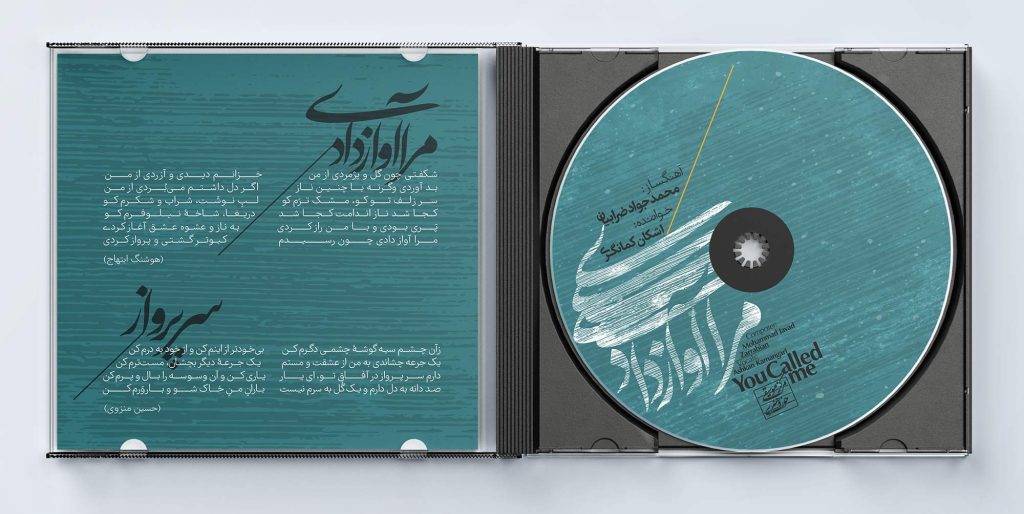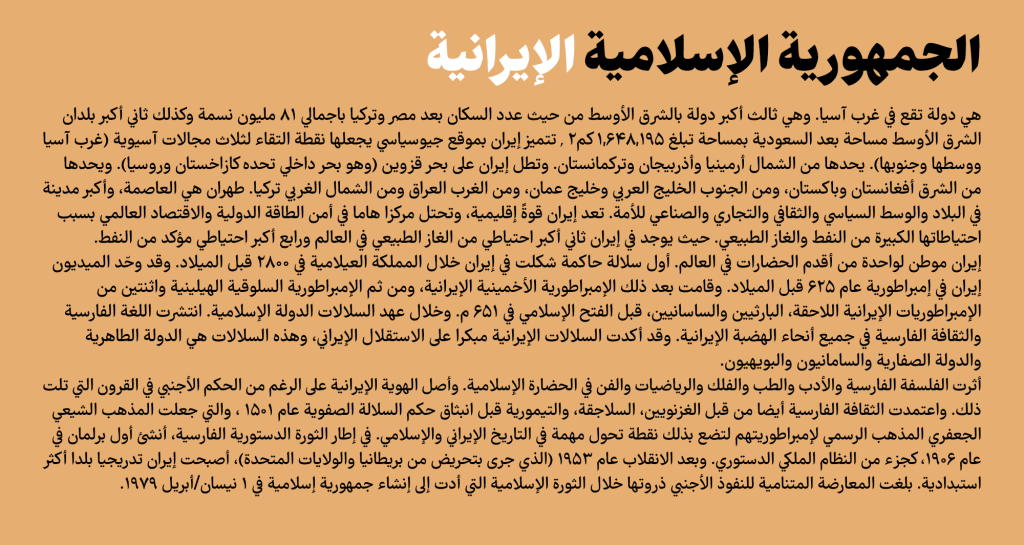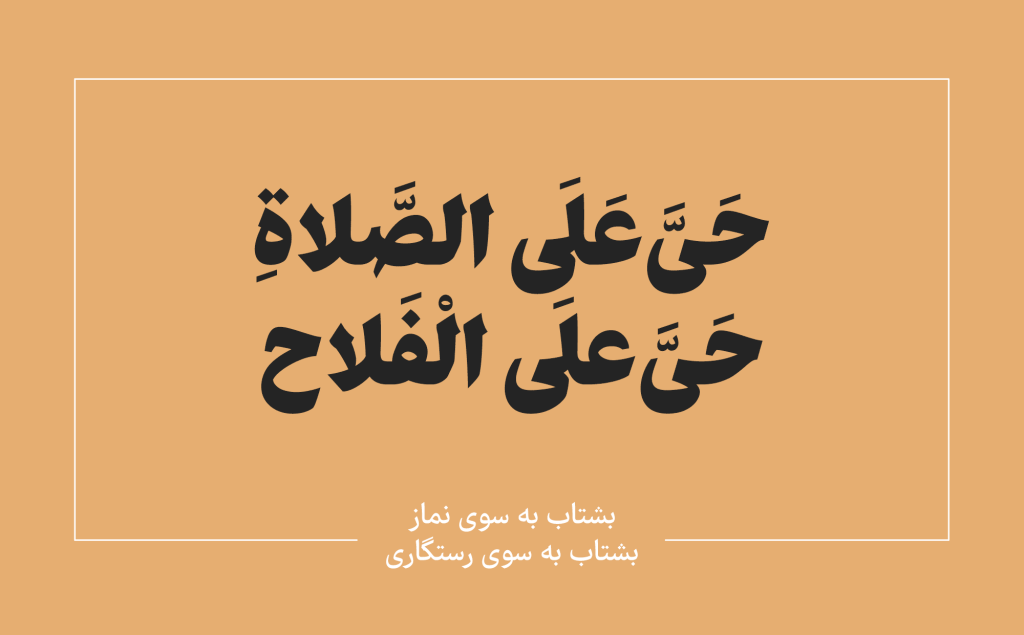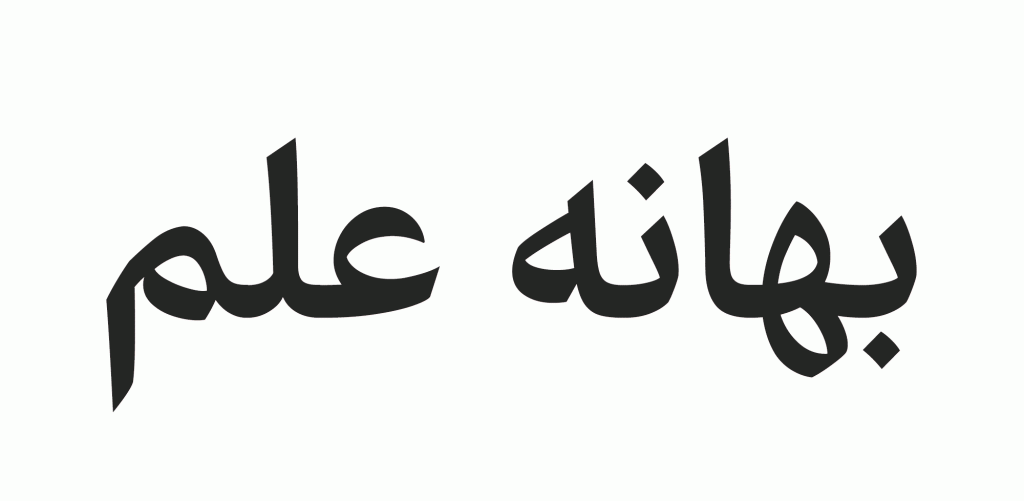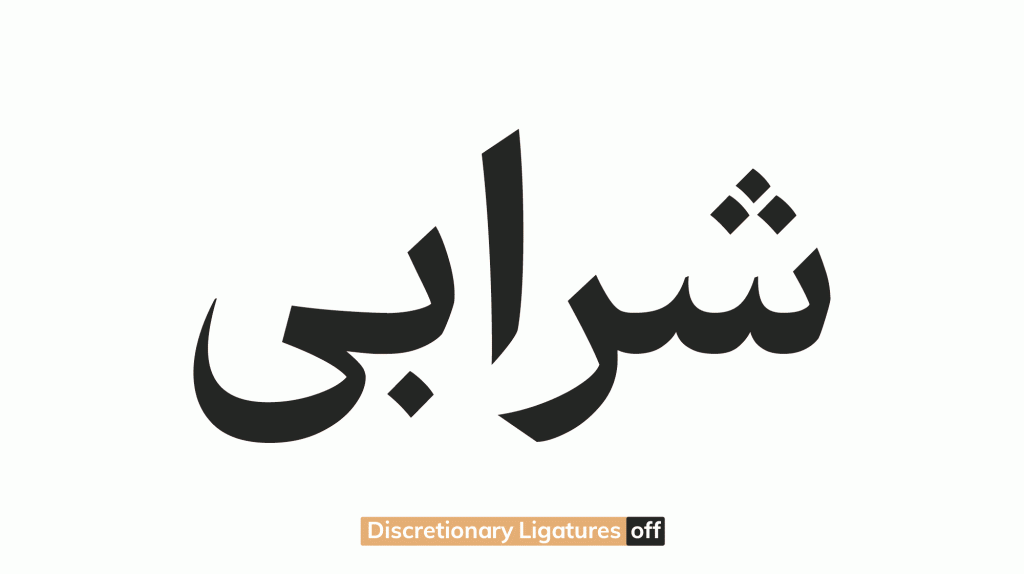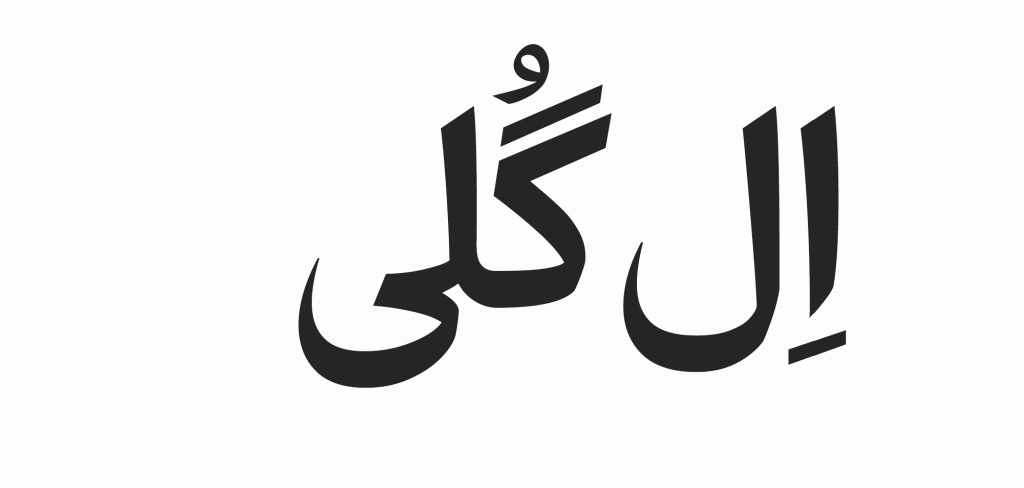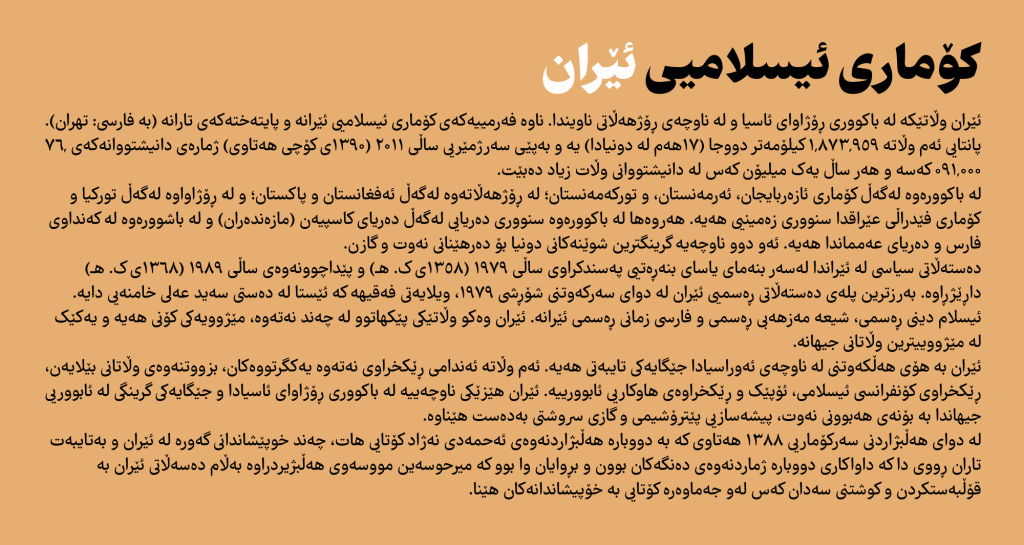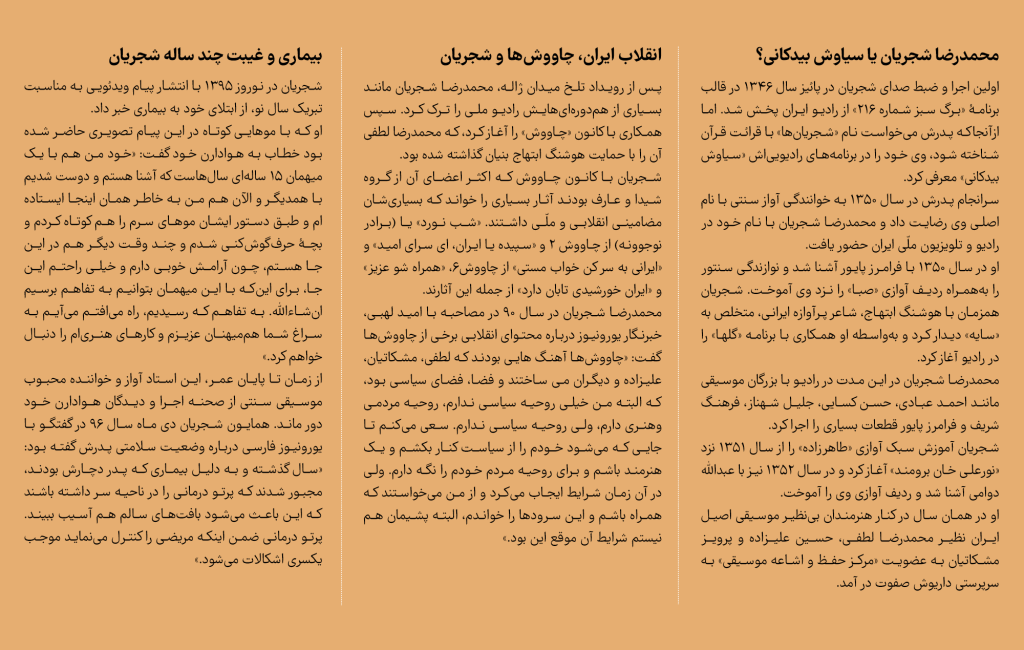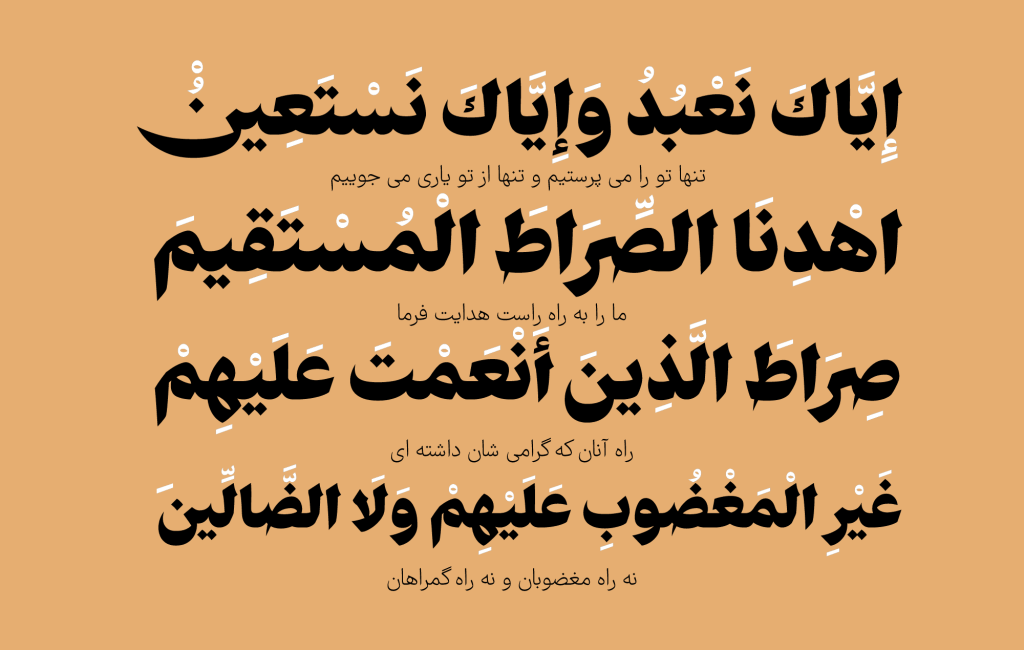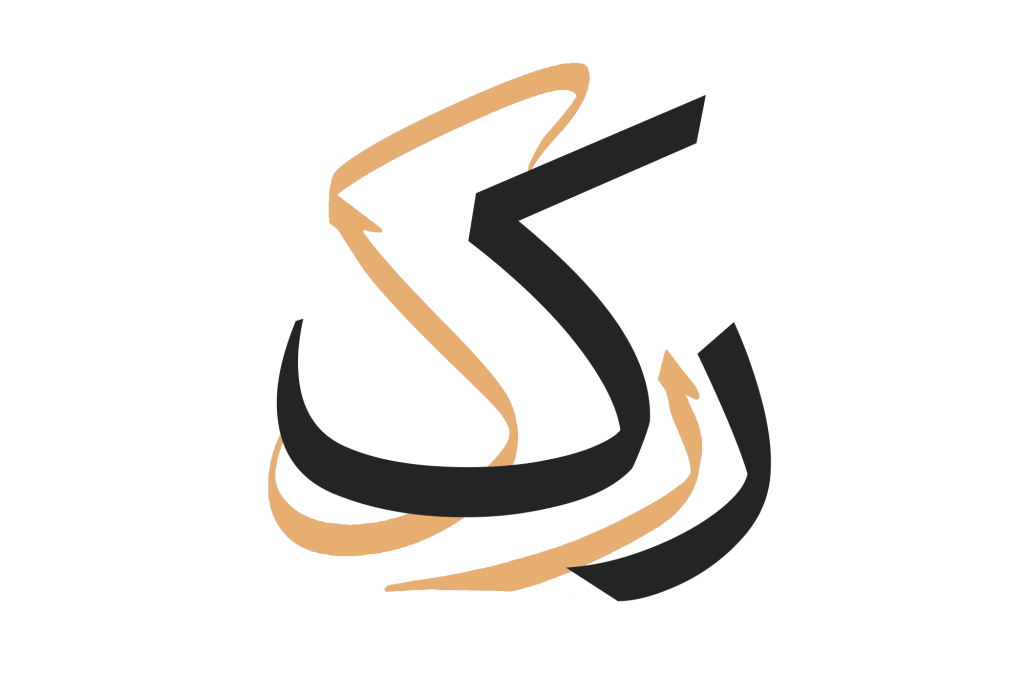
فونت آهنگ
فونت آهنگ قلمی که الهام گرفته از خانواده نسخ و ثلث است توسط آقای مسلم ابراهیمی طراح نام آشنای تایپوگرافی فارسی ایجاد و طراحی گشته است. در واقع این تایپ فیس نسخه بازسازی شده ای از فونت زیبای فرهنگ به همراه 10 وزن متفاوت و بسیاری از امکانات برای شما علاقه مندان و طراحان است.
در بسته دانلود شده این محصول دو سبک یا استایل اصلی و شارپ وجود دارد. آهنگ شارپ در واقع پایه اصلی این محصول زیبا است و فونت آهنگ با تخت کردن و کاهش کنتراست استایل آهنگ ‌شارپ پدید آمده است.
خطاطی و خوشنویسی در قلم آهنگ
از دیر باز حروف  ” ر – ک ” دو حرف پرچالش برای طراحان تایپوگرافی به شما رفته است. چرا که همواره باید مواظب آن بود که تجاوزی به همسایگان خود نداشته باشند. اما در این تایپ فیس به منظور حفظ حس و حال خطاطی و زیبایی کار این حروف یعنی ک و ر ، پاشنه بلند و سرکش هستن بدون  اینکه هرکدوم  پاشو از گلیم خودش درازتر کرده یا سرک کشیده باشن به فضای حرف همسایه.
با دقت در تصاویر نمونه از این تایپ فیس به تفاوت هایی مشهود بین دوسبک از این قلم پی می بریم. آهنگ دندانه‌های تخت دارد، با صلابت و قدرتمند است. در صورتی که آهنگ شارپ (با تیز شدن دندانه‌ها و انتهای حروف) به دنبال حفظ اصالت خطاطی و ظرافت هنری می باشد
در اوزان پایین‌ چندان تفاوتی بین  آهنگ و آهنگ شارپ مشاهده نمی شود و بیشتر جنبه کاربردی دارد. وجود دو استایل متن با کنتراست متفاوت به طراحان این امکان را می‌دهد که با توجه به نوع کاغذ و چاپ یا شرایط نمایشگر دیجیتال نسخه سیاه‌تر (آهنگ) یا نسخه ظریف‌تر (اهنگ شارپ) را انتخاب کنند.
پشتیبانی فونت آهنگ از ترکیبات جایگزین
به منظور ایجاد تنوع و زیبایی دو چندان ترکیبات جایگزین در قلم آهنگ تعیین گردیده است. آهنگ دارای تعدادی از ترکیبات جایگزین و اختیاری است که دست طراحان را برای خلق تنوع و دوری از یکسانی و یکنواختی بازتر می کند. راهنمای فعال‌سازی ترکیبات برای نرم افزارهای گرافیکی و وب در بسته دانلودی موجود است.
همچنین به منظور تزئین و افزایش جاذبه های بصری و دیداری می‌توانید با فعال‌سازی Stylistic set طره‌های تزئینی مروسوم در خوشنویسی نسخ و ثلث را به حروف ا ل لا ک ص‍ ط اضافه کنید. این تایپ فیس گستره زیادی از زبان های مختلف را پشتیبانی می نماید. از جمله این زبان ها می توان به زبان عربی اردو کوردی و … اشاره نمود.
یکی دیگر از مزیت های این این قلم چینش زیبا و دقیق نقطه ها و دندانه ها است. حروفی مانند ب‍ ‍ب‍ ت‍ ‍ت‍ پ‍ ‍پ‍ ث‍ ‍ث‍ ن‍ ‍ن‍ ی‍ ‍ی‍ س‍ ‍س‍ ش‍ ‍ش‍ گروه پر جمعیت خط فارسی هستند که شکل کاملا مشابهی دارند. چشم تنها با تشخیص فواصل و نقطه‌ها آن‌ها را از هم تشخیص می‌دهد. با دقت در تصاویر نمونه این قلم می توانید ببینید نقطه‌ها در جای درست خود یعنی زیر حرف مربوط به آن قرار دارند و دقت و ظرافتی فوق العاده برای این مهم به کار رفته است.
همچنین هر دندانه با توجه به حروف قبل و بعد خود شکل و جای نقطهٔ خود را طوری تعیین می‌کند تا نهایت نظم و زیبایی در شکل کلمات بدست آید.
نسخه وریبل فونت در قلم آهنگ
وریبل فونت تکنولوژی جدیدی است که به شما این قابلیت را می‌دهد که همه‌ی وزن‌ها و استایل‌ها را در قالب یک فایل فونت در اختیار داشته باشید. سرعت بیشتر و حجم کمتر یکی از فواید این تکنولوژی است که بیشتر در وب سایت ها به کار می رود تا تعداد دفعات درخواست به سرور کاهش و سرعت لود صفحات وب بالا رود.